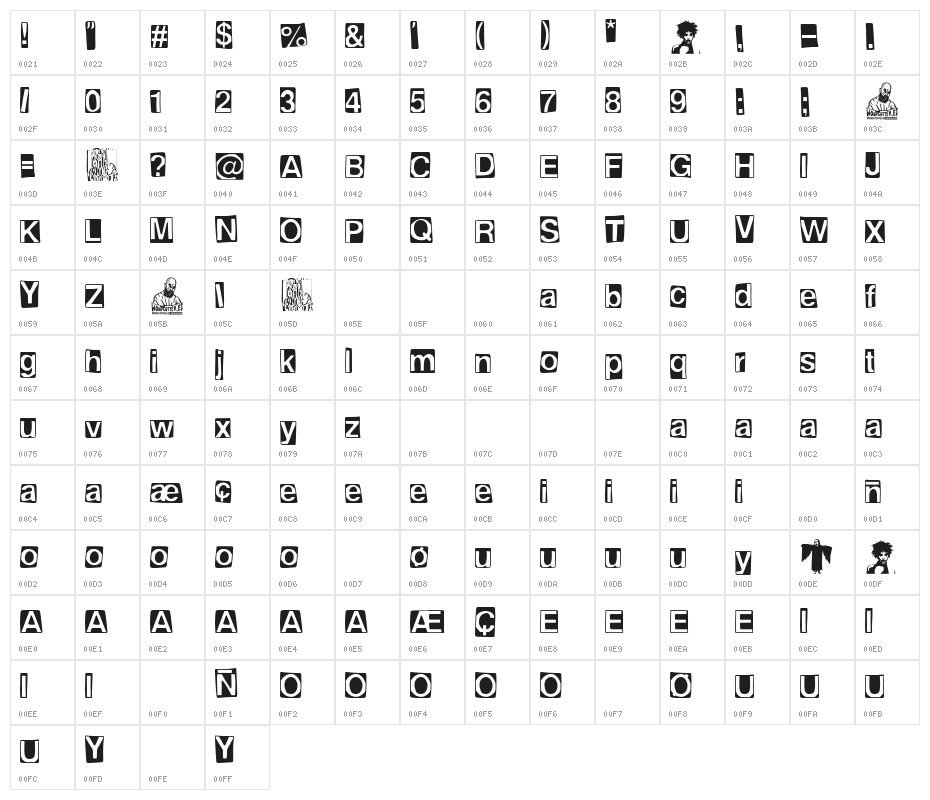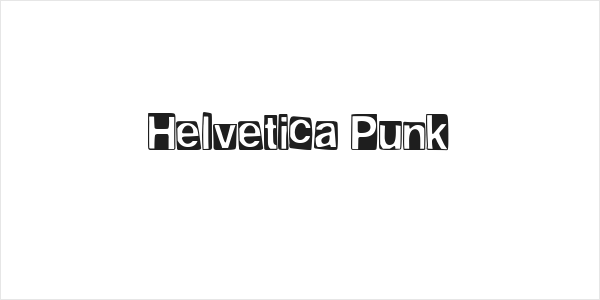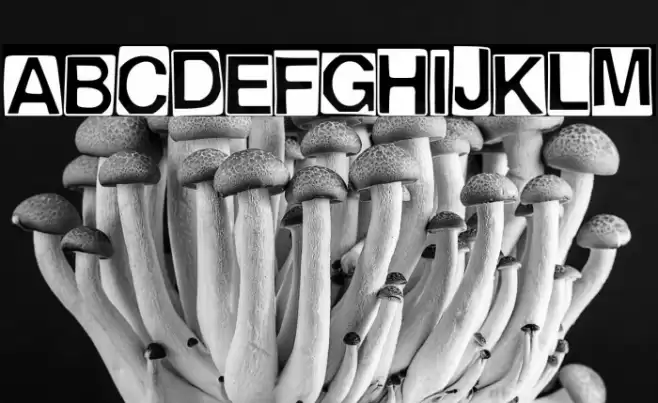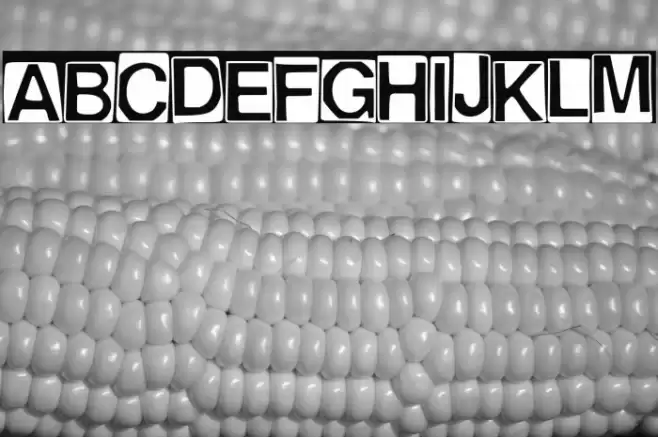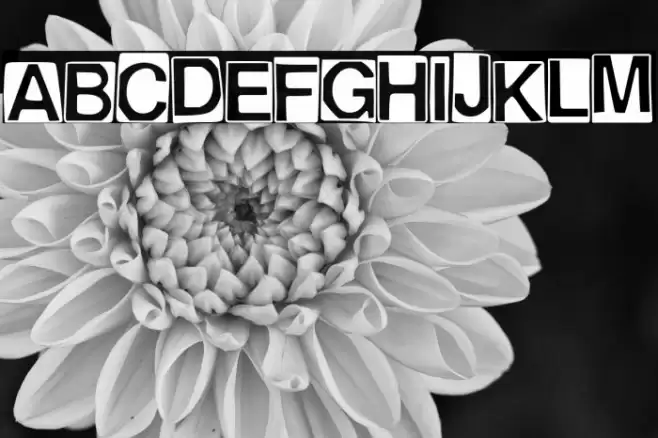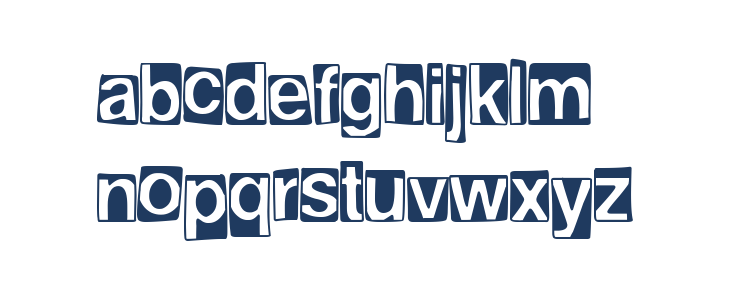
Helvetica Punk Font
| Gesamtstil | Modern, Punk |
| Vorgeschlagene Projekte | Album covers, posters, streetwear branding, zines, and any project needing a rebellious edge. |